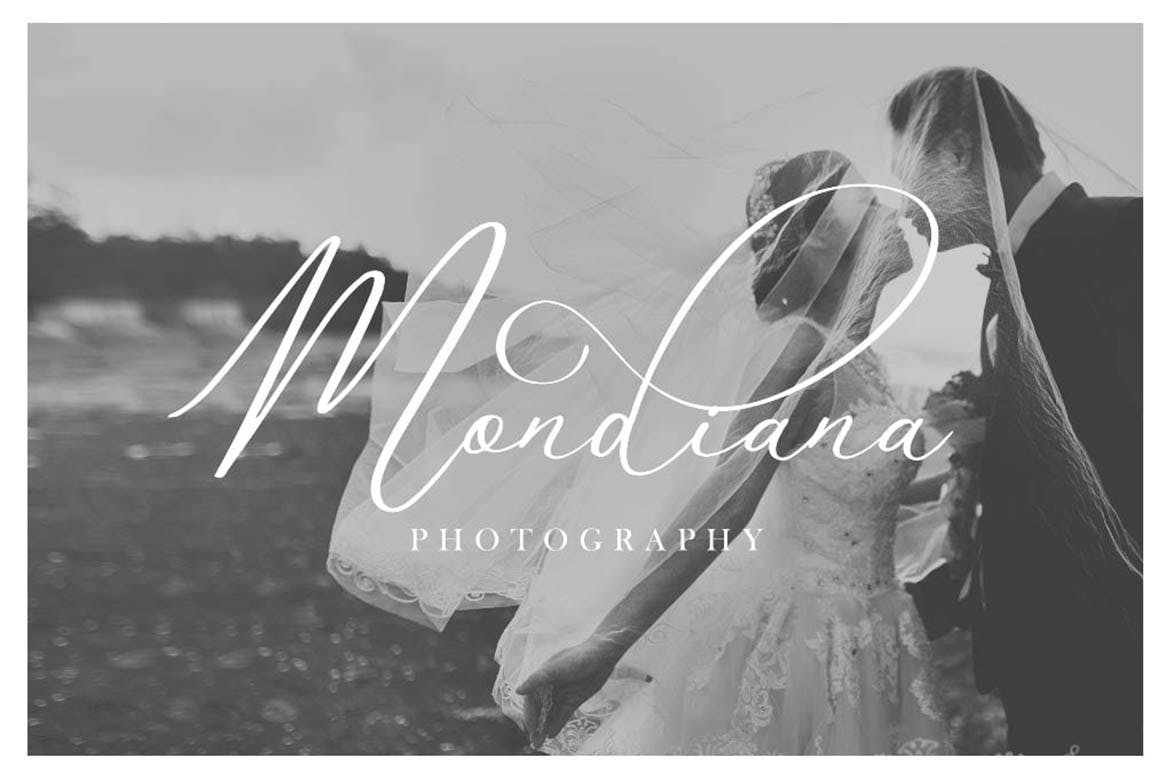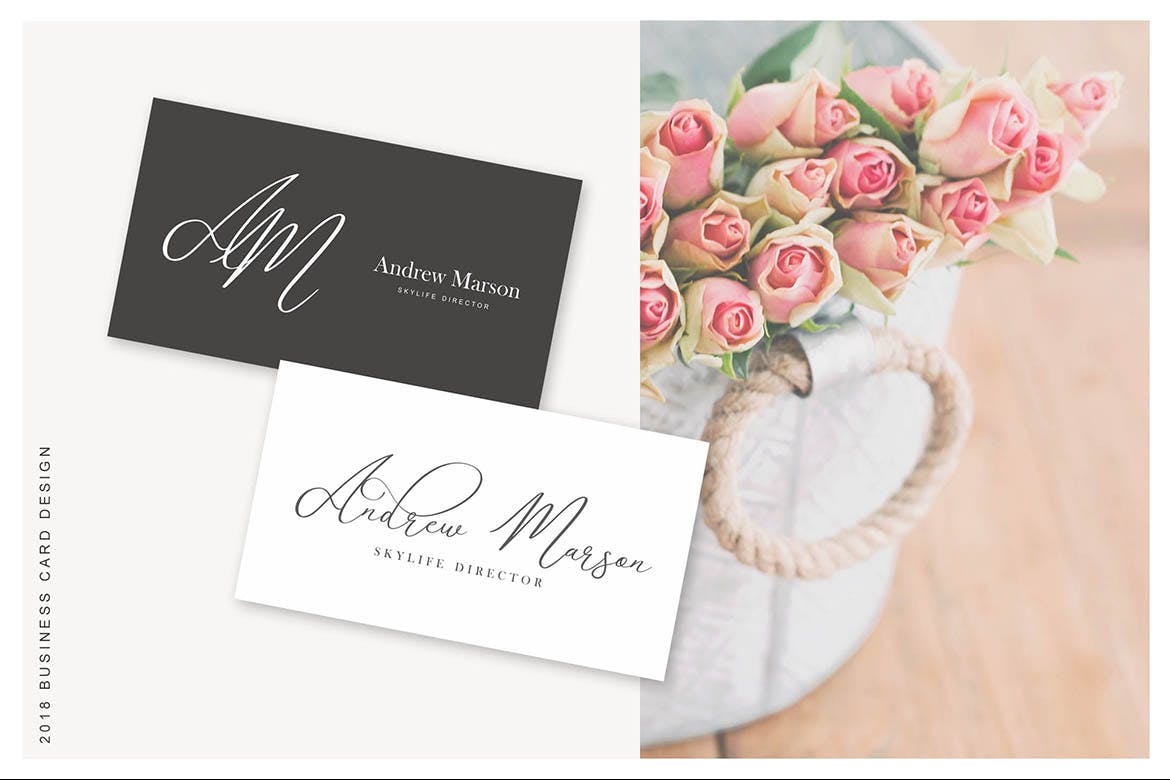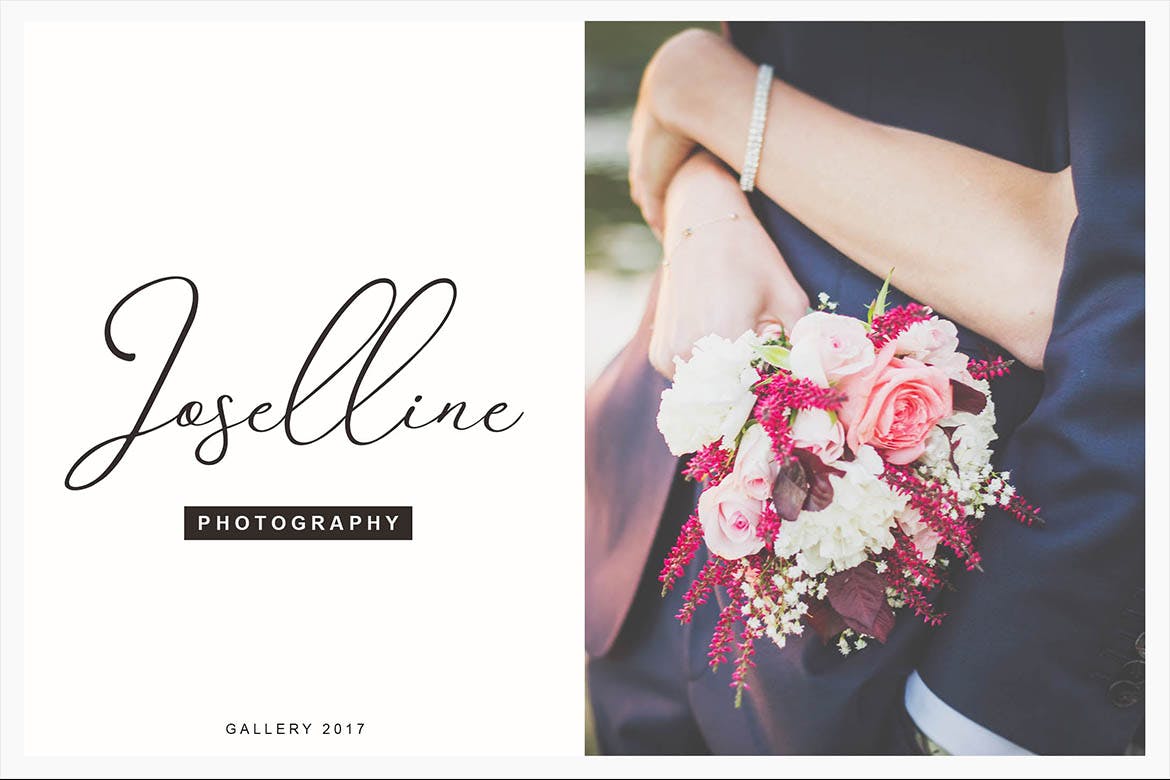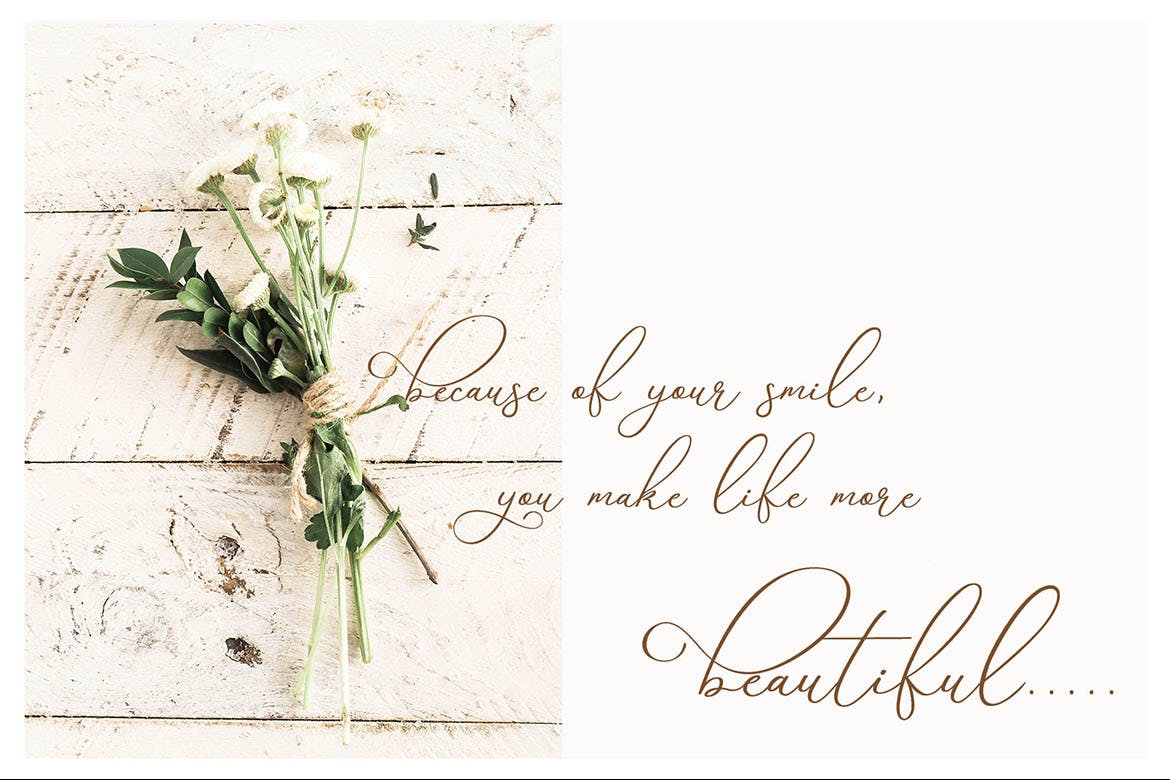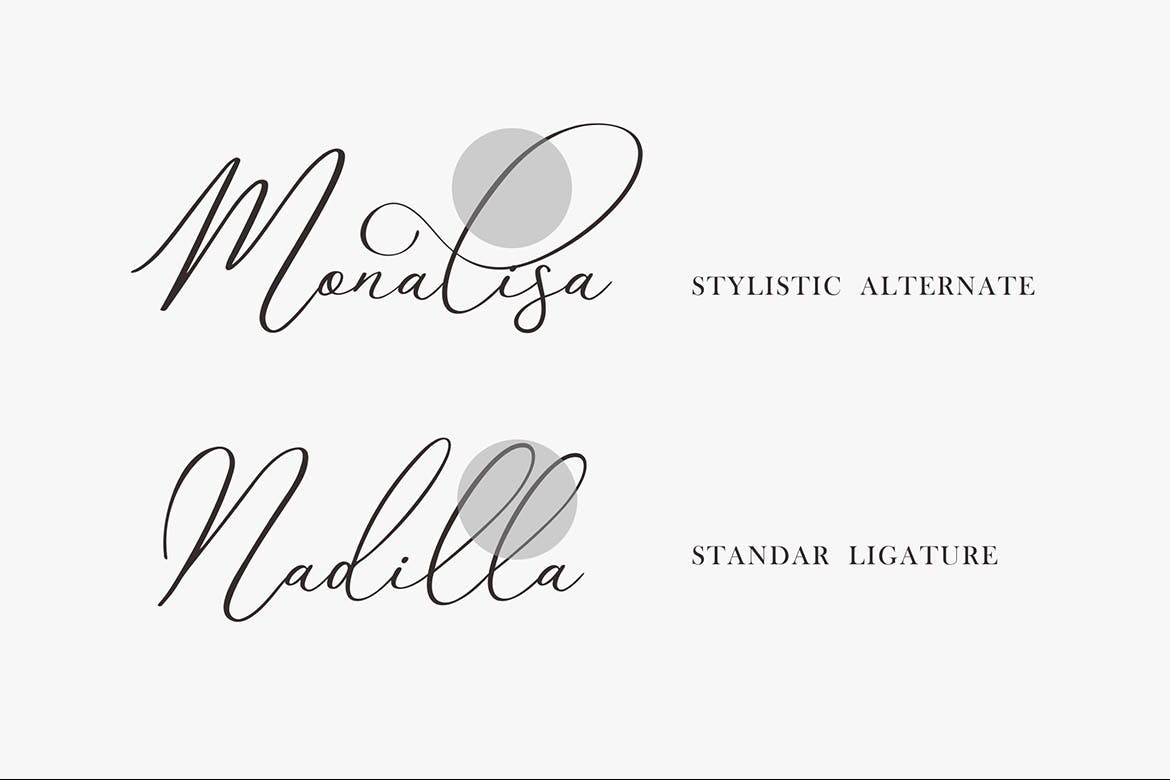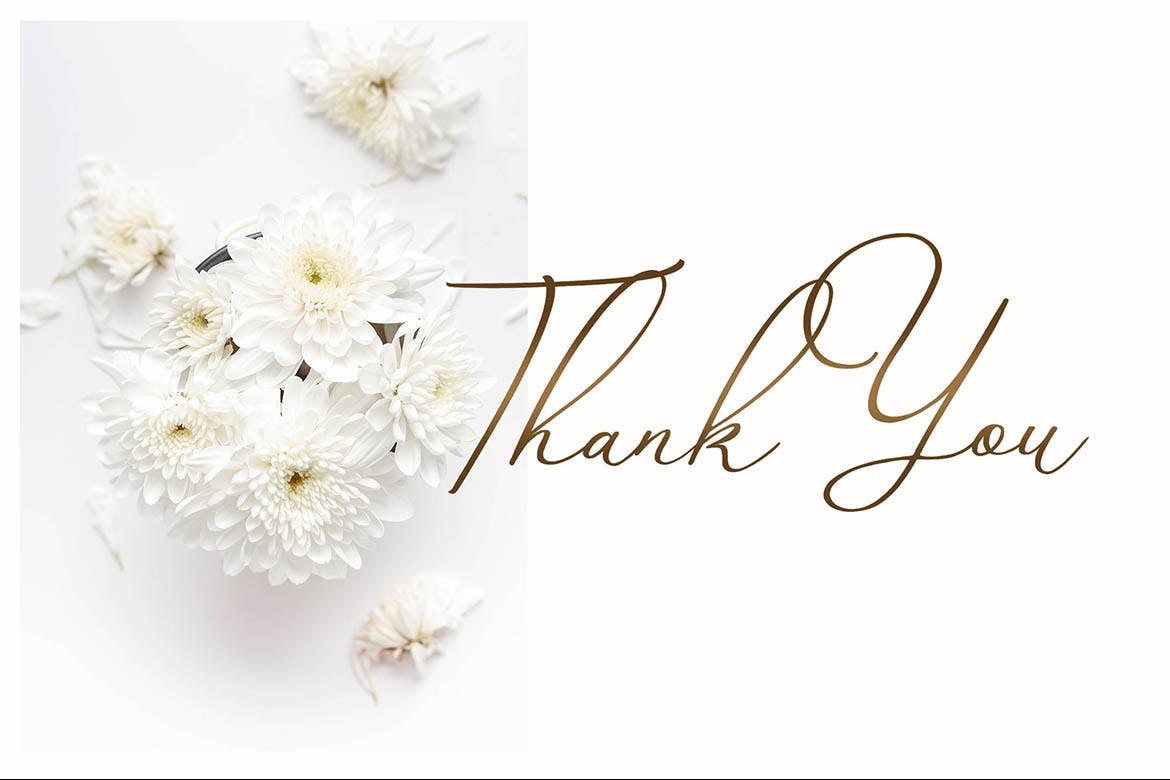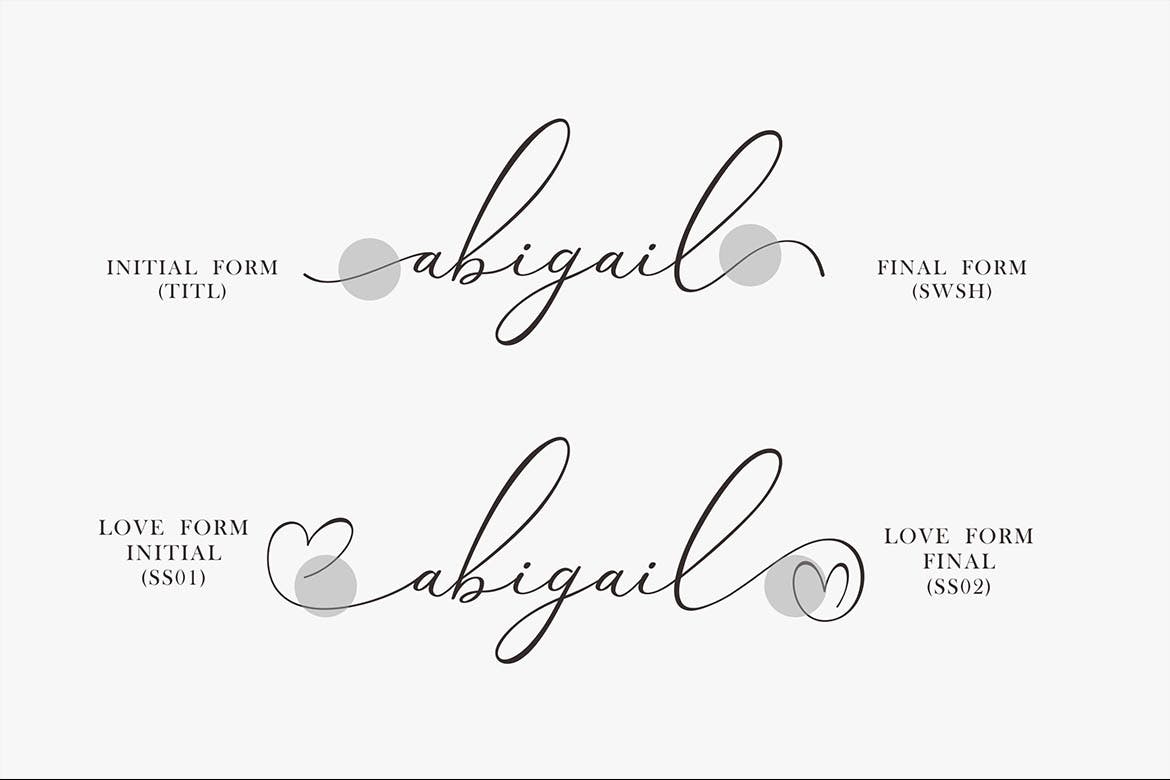
دانلود فونت لوکس Avelline برای طراحی‌های زیبا
Avelline Luxury Font
فونت Avelline با طراحی مدرن مناسب برای پروژه‌های مختلف شما.
فونت Avelline یک فونت کالیگرافی مدرن است که برای پروژه‌های شما عالی است. این فونت مناسب برای امضاهای باکلاس، امضاهای عکاسی، نقل قول‌های زیبا، برندینگ محصولات آرایشی و هر پروژه طراحی زیبایی می‌باشد.
ویژگی‌های فونت Avelline:
• جایگزین‌های استایلی
• لیگاتور استاندارد
• متغیرهای سواش
• حروف کوچک تیتر
• مجموعه‌های استایلی SS01 و SS02
• پشتیبانی چند زبانه